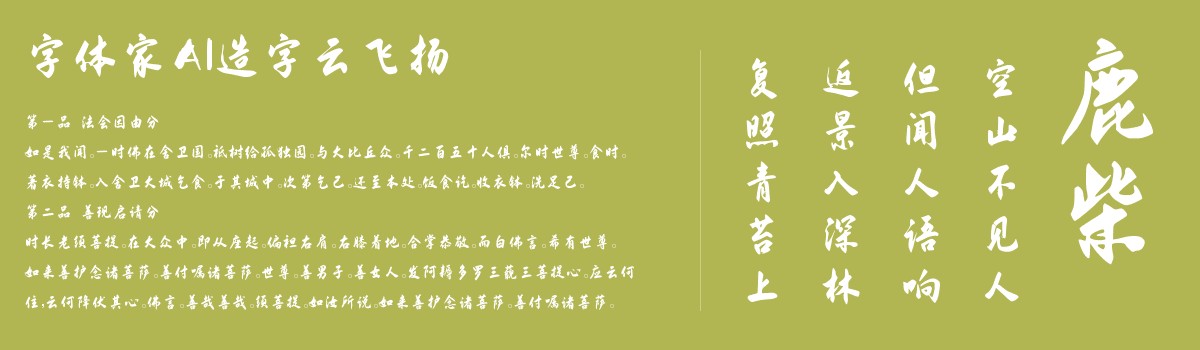
字体家AI造字云飞扬
字体家AI造字云飞扬是一款由字体家AI神笔造字生成的一款书法字体,此字体为手写风格,笔画流畅连贯,存在自然连笔。线条粗细有细微变化,起收笔处略带顿挫感,中段过渡顺滑。单字结构略带倾斜,重心稍偏,显灵动。无刻意规整,保留书写时的自然动态。比较适合用于艺术类装饰文字,海报、网页、广告设计,室内装饰,平面标题设计、食品包装、品牌标志等。